– ワークショップと、美しい活版印刷とカリグラフィーのペーパーアイテム –
今年で第3回目となる「活版印刷とカリグラフィー」を名古屋栄三越にて開催いたします。
東京と大阪を中心に活躍中の、活版印刷とカリグラフィーのクリエイター11組が名古屋に集結します。
歴史ある活版印刷によるペーパーアイテムやアート作品、美しい文字表現が魅力のカリグラフィー作品など、現在活躍中のプリンターやカリグラファーによるステーショナリーをご用意しております。
また、人気カリグラフィーショップ<Paper Tree>がセレクトした、欧米の老舗ブランドや注目デザイナーによる洗練されたツールやステーショナリーも取り揃えました。
会期中は、活版印刷やカリグラフィーのワークショップも開催いたします。印刷と手書きが織りなす豊かな文化に触れながら、その魅力をぜひご体感ください。
参加ブランド – 作品の一部をご紹介 –
Echos Design & Letterpress
Botanical Greeting Card
型抜きカードにカラフルな花々を活版印刷したグリーティングカード。セットの封筒の色味で選ぶのも楽しいです。
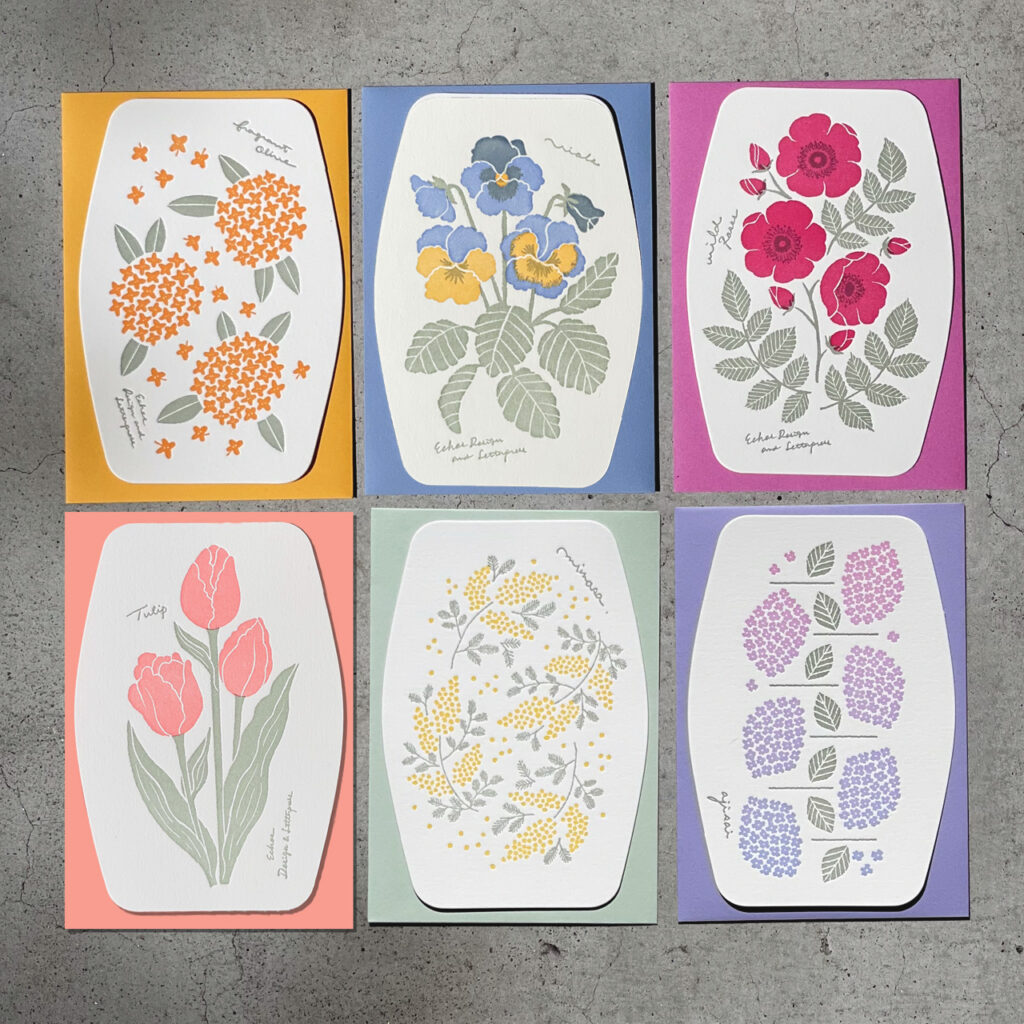
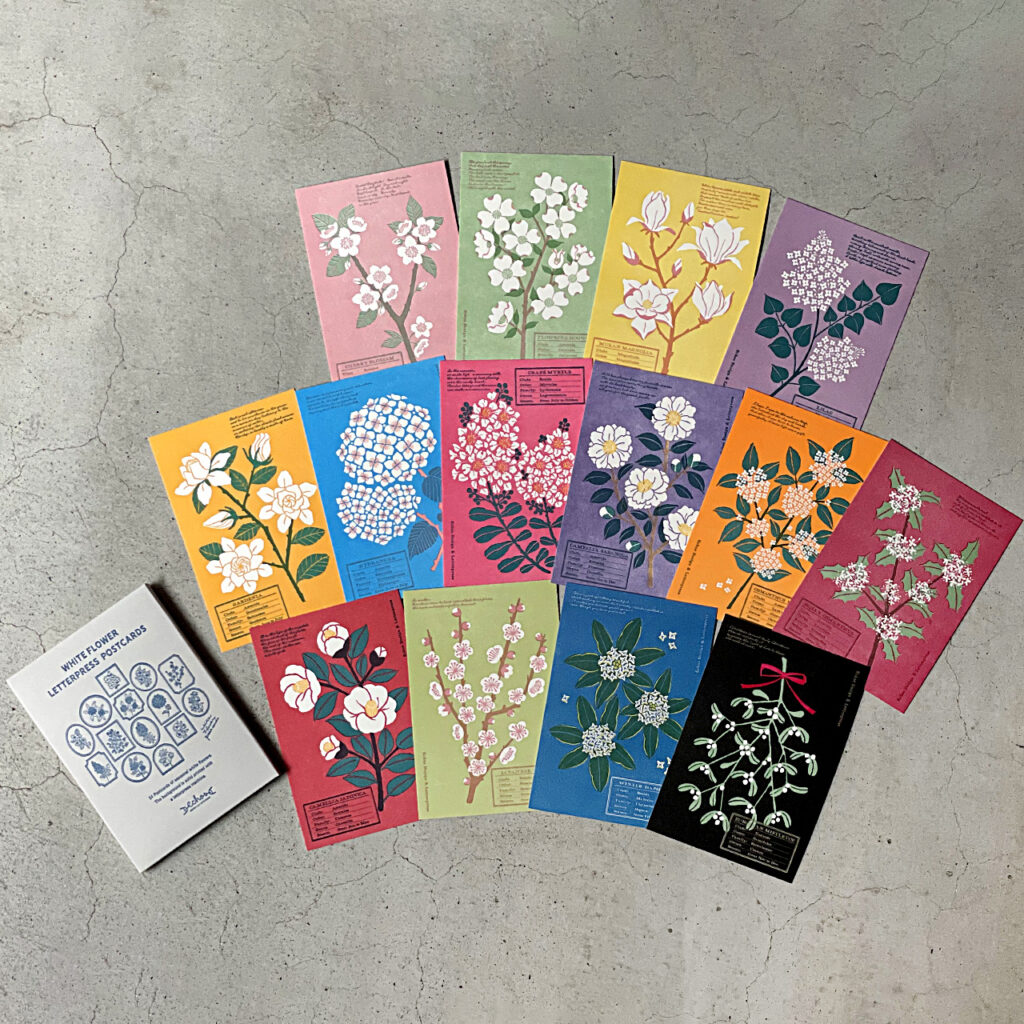
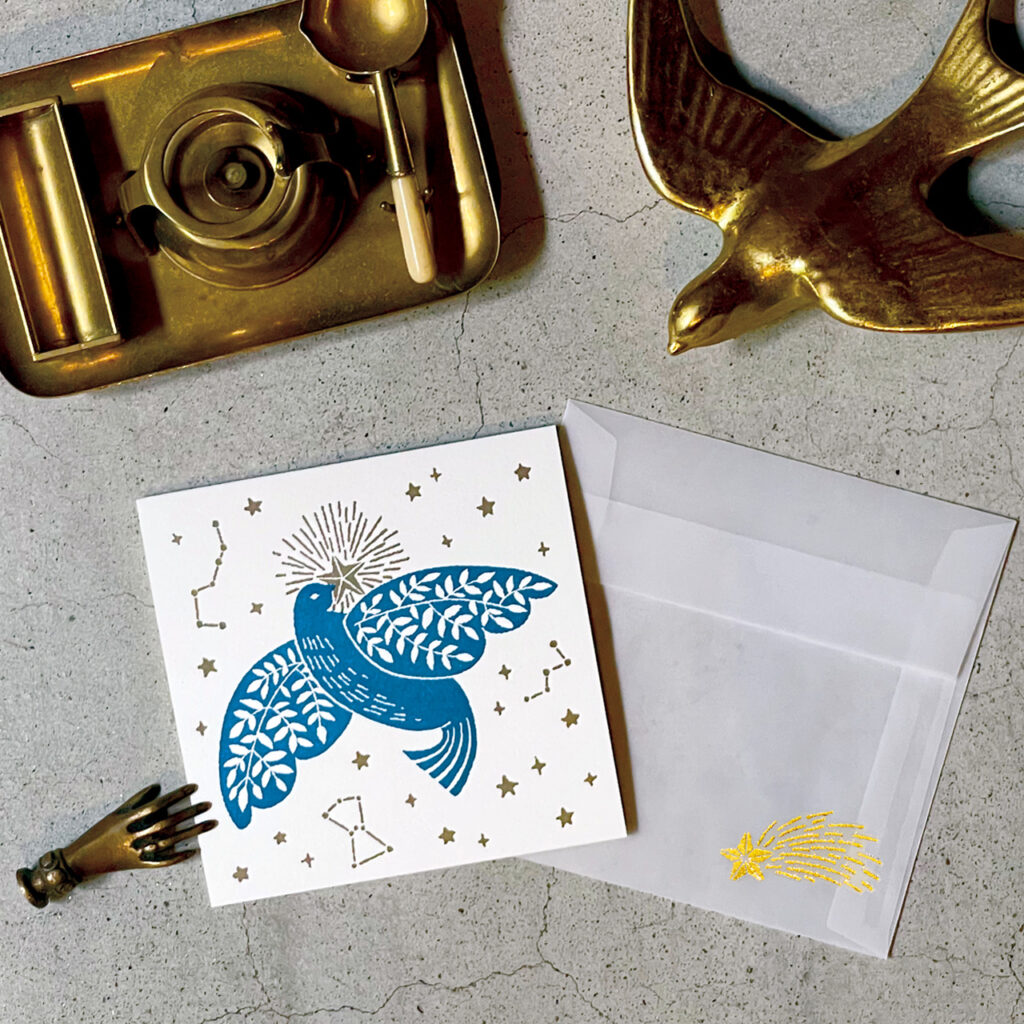
OEDA LETTERPRESS
Label book各種
大枝活版室を代表する商品であるLabel bookは、繊細なデザインが活版印刷の技術によって表現されています。ミシン目が入っていて切り取ることもでき、小さなパーツに分けると、メモはもちろん、コラージュなどにも使用できる万能なアイテムです。
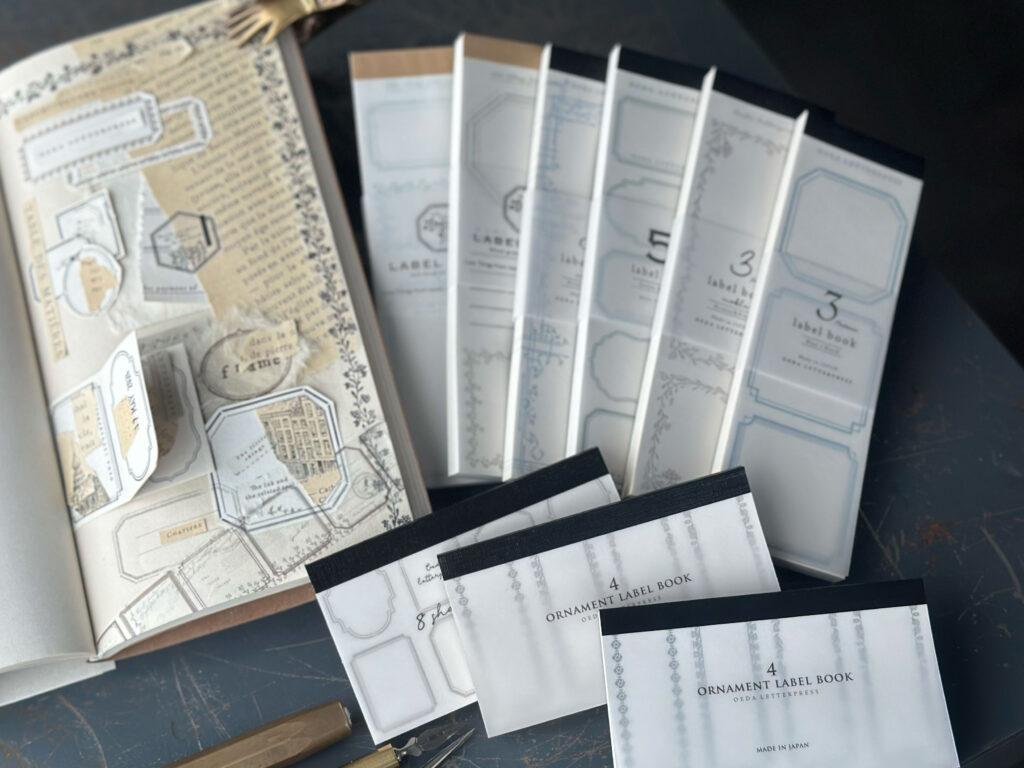
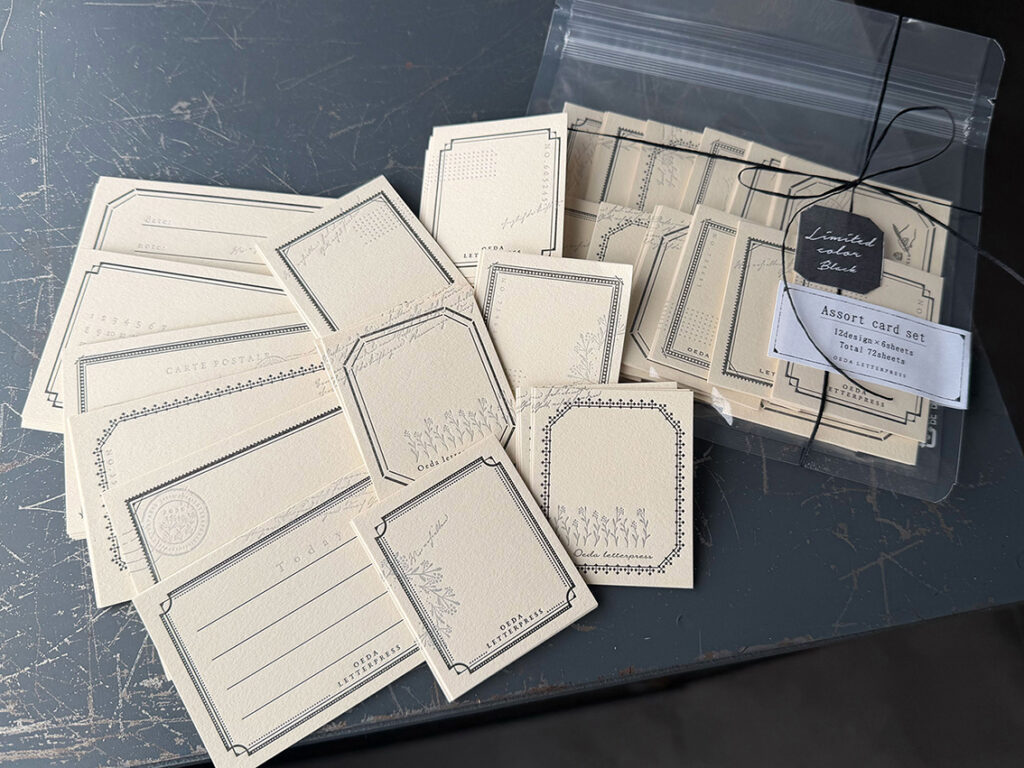
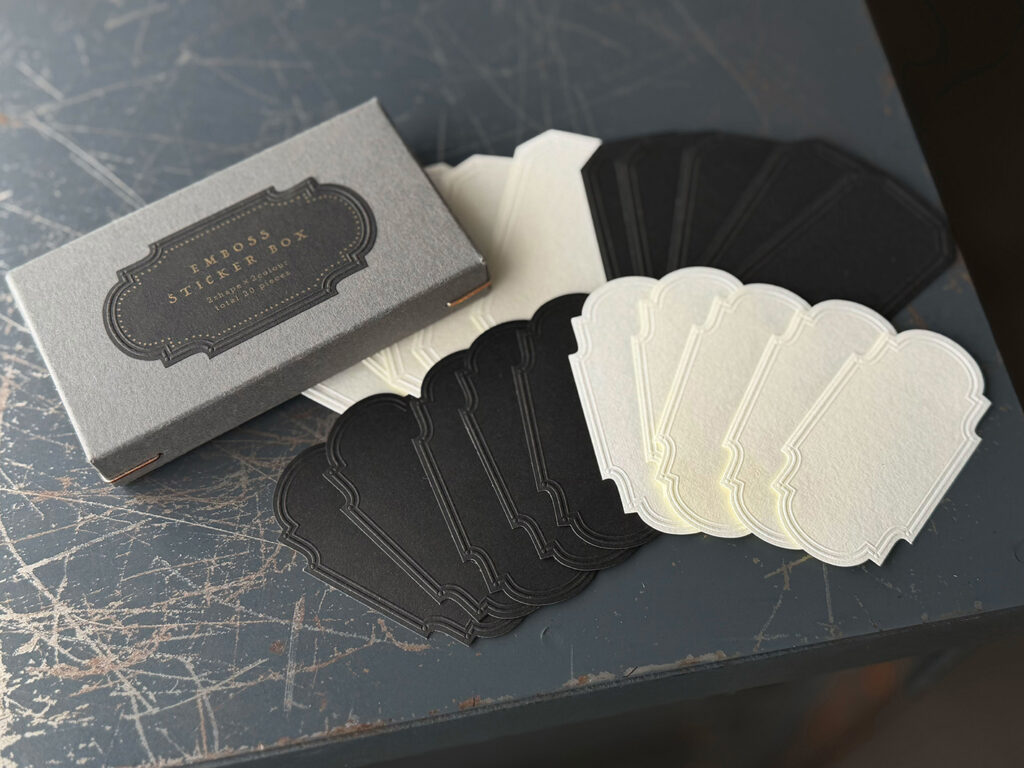
九ポ堂
夜の夢薬局
「少し不思議」な紙雑貨を制作する<九ポ堂>。
物語性があり、みなさんにクスッとしていただける物作りを心がけています。
夢に特化した薬局のハガキ。文字の部分は活字を使用しております。
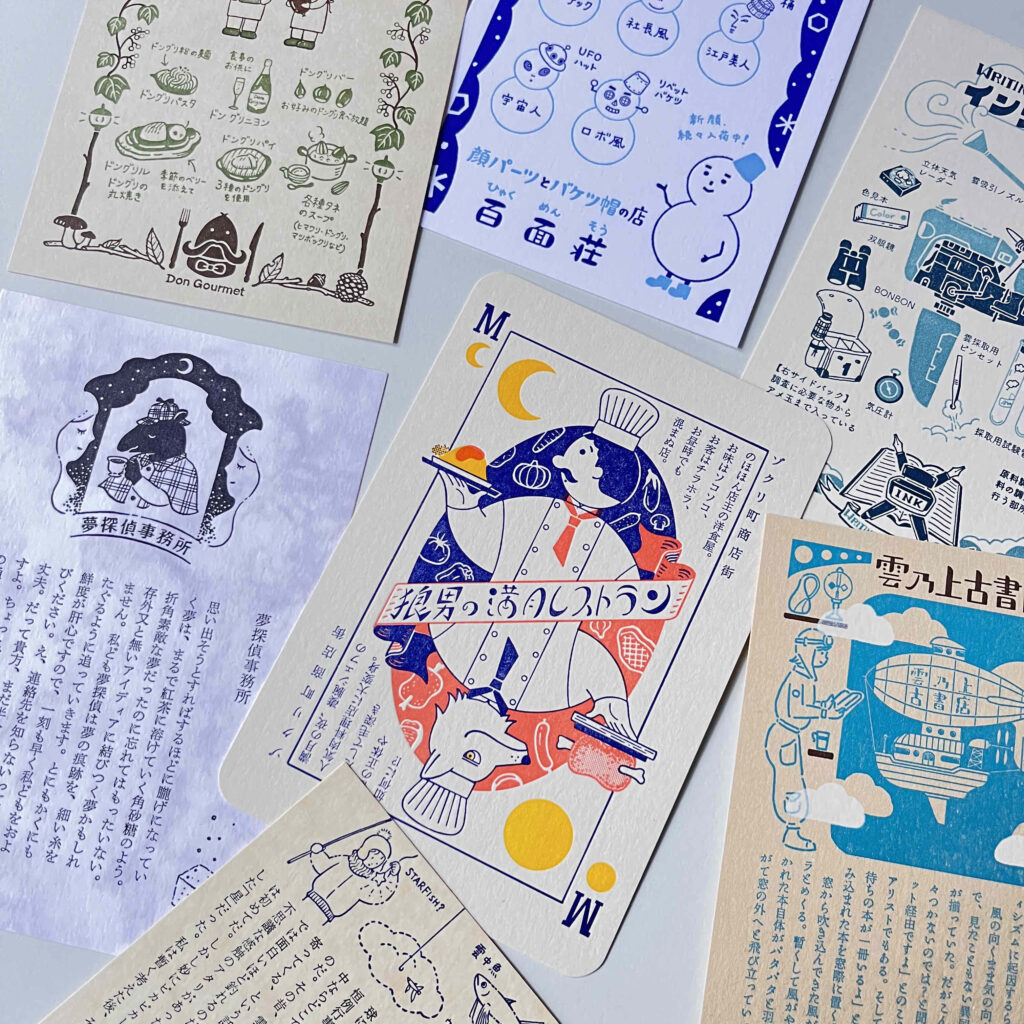
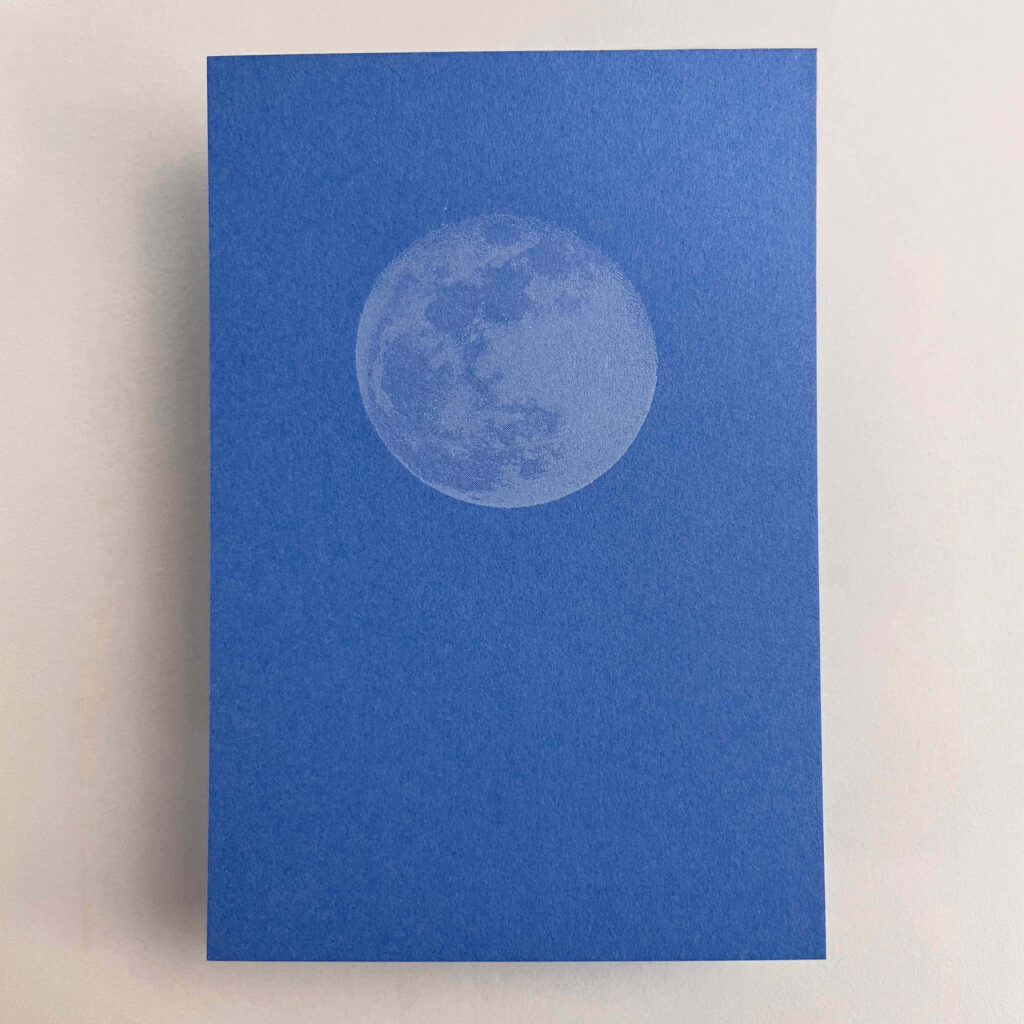
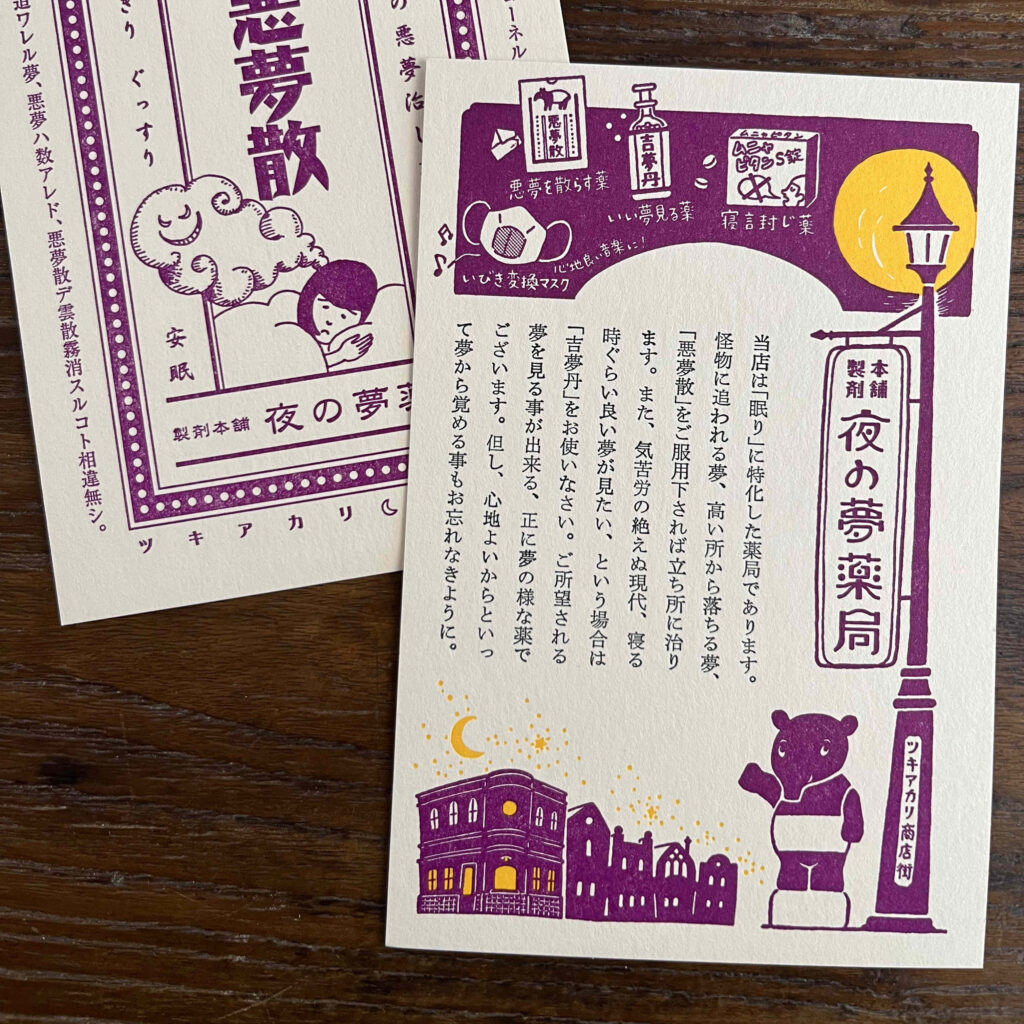
knoten letterpress
ポストカード「彗星」
夜空に現れた彗星。
その姿を一目見ようと、静かに胸を高鳴らせ多くの人々がコメットハンターになる夜の期待と好奇心に満ちた時をとじこめたポストカードです。
暗闇が深くなると星のようにも見える地上の灯りは、彗星・星たちと同じ銀色、風景は墨色の活版印刷2色刷り。ほんとうの彗星を見逃した夜から誰かと小さな彗星を共有したくてあたためていた図案です。紙色違いで印象が変わるそれぞれの夜をお楽しみください。
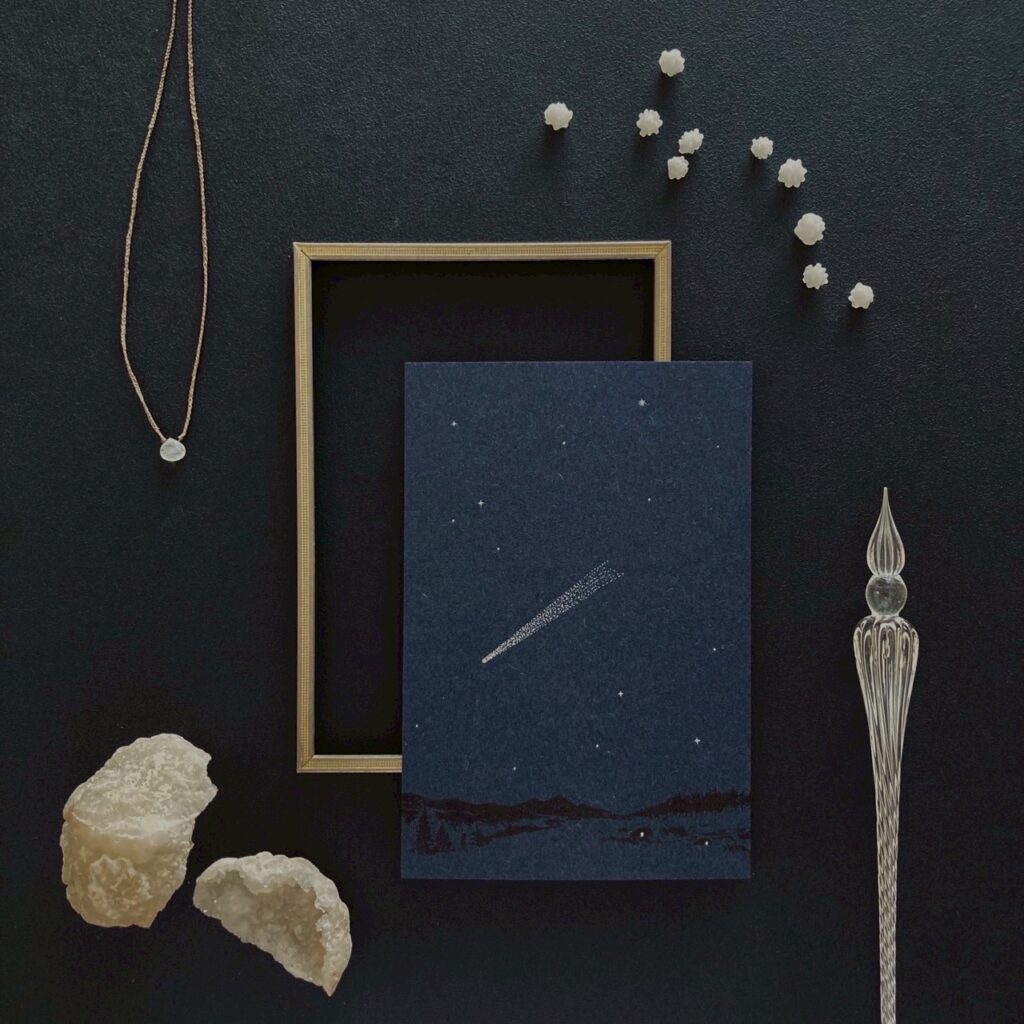
つるぎ堂
雨天結構ポストカード
梅雨の時期、雨続きで憂鬱になるものです。でも、このポストカードがあれば大丈夫。雨の日も結構楽しく過ごせます。
原田祥子
夢叶だるま
日本一の生産地として知られる群馬県高崎市のだるまは、伝統的な縁起柄として「眉に鶴、鼻から口ひげにかけて亀」を描き、長寿や幸福を表現しています。
その高崎だるまモチーフに、「つるかめ」の文字をモダンにデザインしました。お腹の部分には「夢」の文字が入り、願いを込めて一つひとつ丁寧に描いています。
Bird Design Letterpress
箔押し活版イヤーカード HORSE
2026年の干支「馬」を金箔で仕上げたイヤーカードです。官製はがきより少し大きめのサイズで額装して飾るのもおすすめです。カードには馬にちなんだメッセージが描かれています。
Breeze Paper Design
カリグラム箔押しミニカード
バレエの演目からインスピレーションを得て、白鳥やバレエチュチュのモチーフを、流れるような文字だけで描いたカリグラムのミニカード。繊細なラインが描く優雅な世界に、上質な箔押しがきらりと輝きを添えます。
大切なギフトに添えるタグや、小さなメッセージカードとしてもおすすめです。
Paper Tree
東京都・千代田区に店舗を構えるソーシャルステーショナリー&カリグラフィー専門店<Paper Tree>。
欧米の老舗ブランドや注目デザイナーによる洗練されたツールやステーショナリーをはじめ、カリグラフィーアイテムを中心に厳選したアイテムをご紹介いたします。
増本 綾
ICY MOON
何十年も前に収録されたライブレコーディングアルバムから聞こえるグラスが触れ合う音、控えめな笑い声、誰かの咳。それは名演奏を生で聞く幸運に恵まれた人々の息遣いが偶然にも音源に刻まれたもの。それと同じように私の愛する京都のジャズーバーが溶けない氷として時を越えて残り続けることを祈りこの本を活版印刷で作りました。
和綴本・エディショナルナンバー付
ゆり華
お祝いをカップケーキに乗せて
カリグラフィーで綴られた英語と日本語を組み合わせた<ゆり華>のバースデーカード。
全体のフォルムは、キャンドルを灯したカップケーキをイメージしています。トップには「祝」の文字をそっと添え、1画目がキャンドルの炎のように立ち上がるデザインに。全体を柔らかく照らすような印象で、贈る気持ちをあたたかく包みます。
ピンクの紙にゴールドの箔押しが映える華やかな1枚。そのままインテリアとして飾っても楽しめるカードです。
活版印刷ワークショップのご紹介
ご自身の手で、ノートづくりを楽しんでみませんか。
今を活躍するカリグラファー・クリエイターによる、特別にご用意いただいたカリグラフィーのノートを作成します。
ドイツの活版印刷機「ハイデルベルグプラテン」で印刷した表紙からお好きなデザインを選び、ペールブルーの中紙とともに、スパイラルリングで綴じて仕上げます。短時間で簡単に楽しめるワークショップです。
また、表紙デザインの中には、原田祥子さん、Breeze Paper Designさん、Paper Treeさん、ゆり華さんとのコラボレーション作品も登場します。活版印刷とカリグラフィーが出会って生まれたイベント限定デザインの中から、お気に入りの表紙を見つけてみてください。